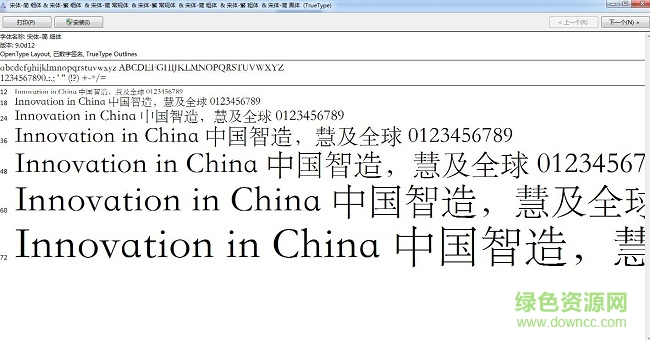
宋體gb2312字體
宋體gb2312是什么字體?宋體gb2312怎么安裝?宋體gb2312字體也就是國(guó)標(biāo)宋體,收字為6763個(gè),一般的微軟office辦公軟件里自帶的就是這款宋體,需要的朋友歡迎前來(lái)下載!
宋體字體命名由來(lái)
康熙十二年,敕廷臣補(bǔ)刊經(jīng)庵《文獻(xiàn)通考》的序文中,規(guī)定:“此后刻書,凡方體稱宋體字,楷書均稱軟字”?!八误w”之名,乃清朝康熙皇帝指定。這命名是有問(wèn)題的,除了“宋體”非宋,歷代隋、唐、宋、元的刊本字樣也各有特色,卻一概劃作一類。然而皇帝之令,不能不從,中國(guó)文人自此習(xí)稱明代刊本字作“宋體”。